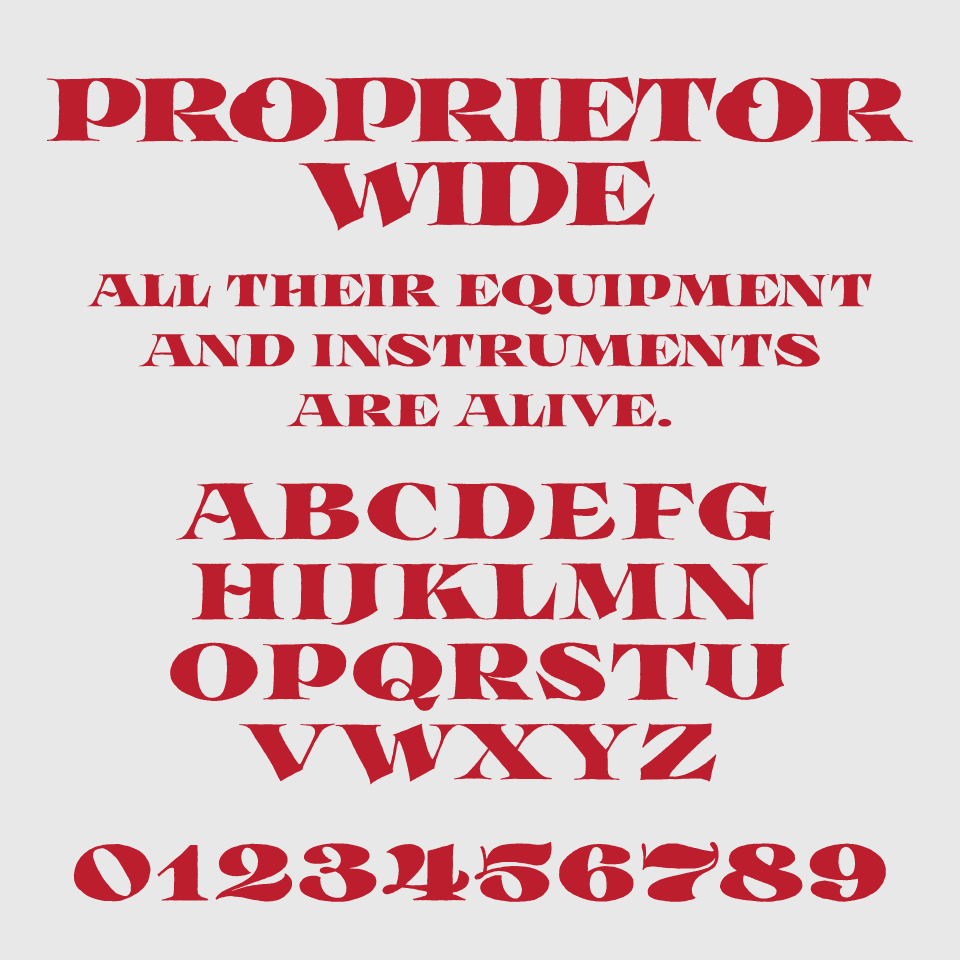
Proprietor Wideフォントは、魔法、超自然現象、異世界などのファンタジー映画のような物語を感じるられるクラシカルで力強いセリフ体フォントです。
重厚なウェイトと、荒削りなようでいて絶妙に整ったバランス感が共存し、骨太ながらもどこかアーティスティックな雰囲気があります。
歴史や伝統を感じさせながら、かすれ感などのアナログ感や人間味も残しており、現代的なクラフト系デザインとの相性も抜群です。
収録文字は、大文字/数字/記号の収録となっています。